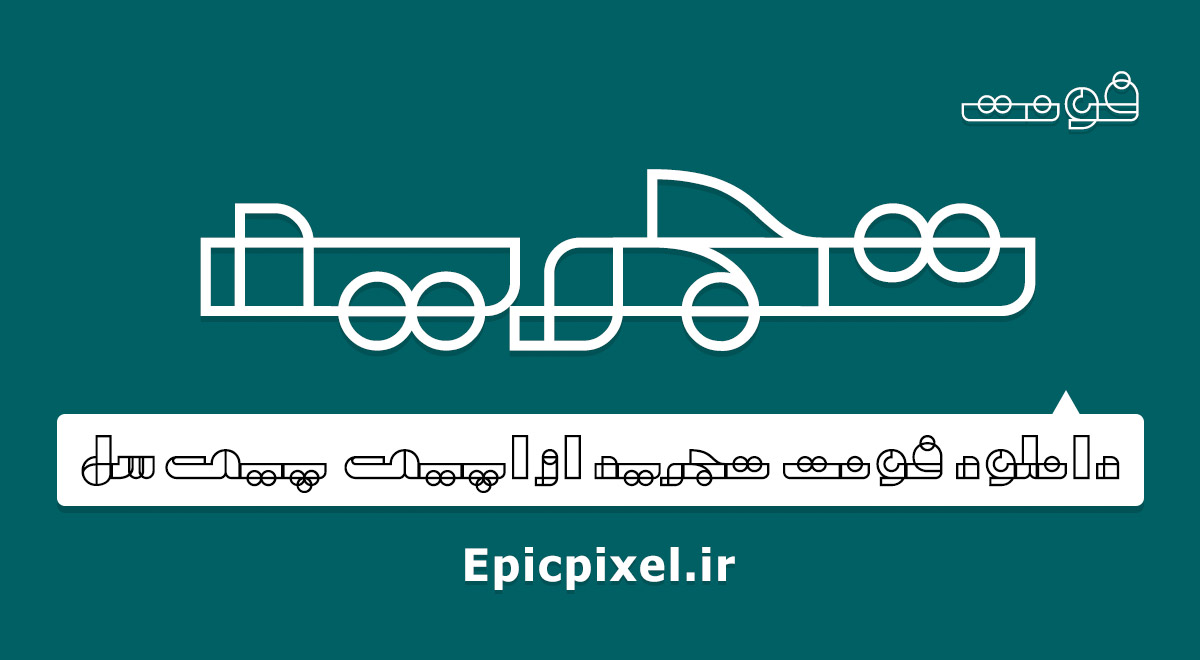
فونت تجرید، یک انتخاب هوشمندانه برای طراحان و صاحبان کسب وکاری است که به دنبال ظاهری مدرن و در عین حال رسمی برای نوشته های فارسی خود هستند. این فونت با طراحی منحصر به فرد خود، خوانایی بالایی را در اندازه های مختلف، چه در صفحات وب و چه در متون چاپی، ارائه می دهد. ساختار حروف در تجرید به گونه ای است که چشم را خسته نمی کند و تجربه کاربری بهتری را برای مخاطب فراهم می سازد.